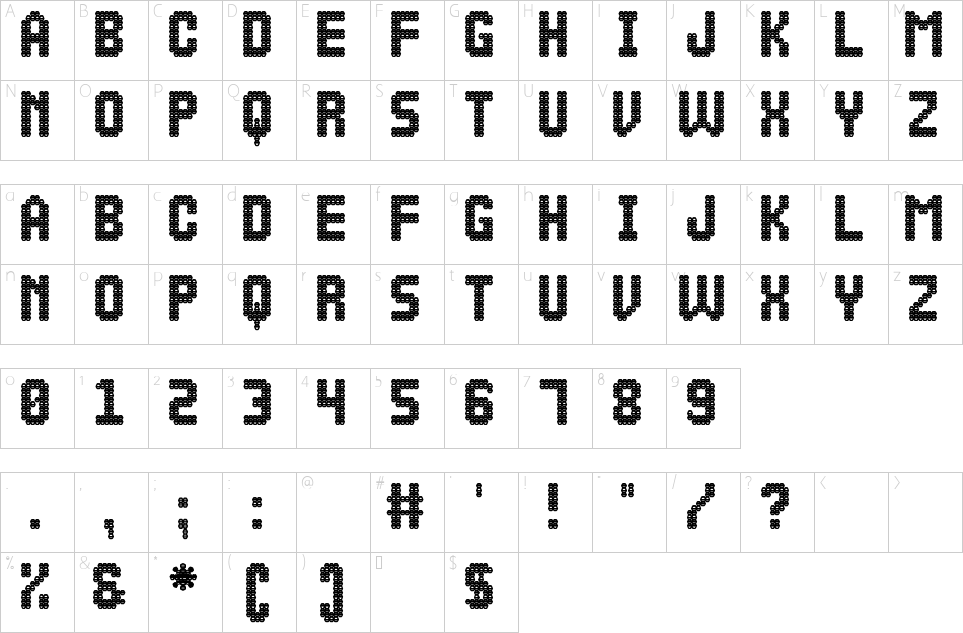
A fonte “Mala Vida Font” é uma escolha perfeita para aqueles que valorizam uma mistura de elegância e ousadia na tipografia. Designada por um criador desconhecido, a “Mala Vida Font” oferece um estilo único que combina elementos de diferentes estilos, criando uma sensação vibrante e moderna. Esta fonte foi projetada para atender aos requisitos de estilos variados, desde textos simples até designs mais elaborados, garantindo uma experiência visual atraente e funcional. Com uma elegância discreta e uma paleta de cores que complementa os mais variados ambientes, a “Mala Vida Font” é uma opção ideal para designers e criadores de conteúdo que buscam uma fonte gráfica de alta qualidade. Com mais de 6.600 downloads, é evidente que esta font é uma escolha popular, que está disponível tanto para sistemas Windows quanto Mac. A “Mala Vida Font” é uma fonte gratuita que merece uma chance.